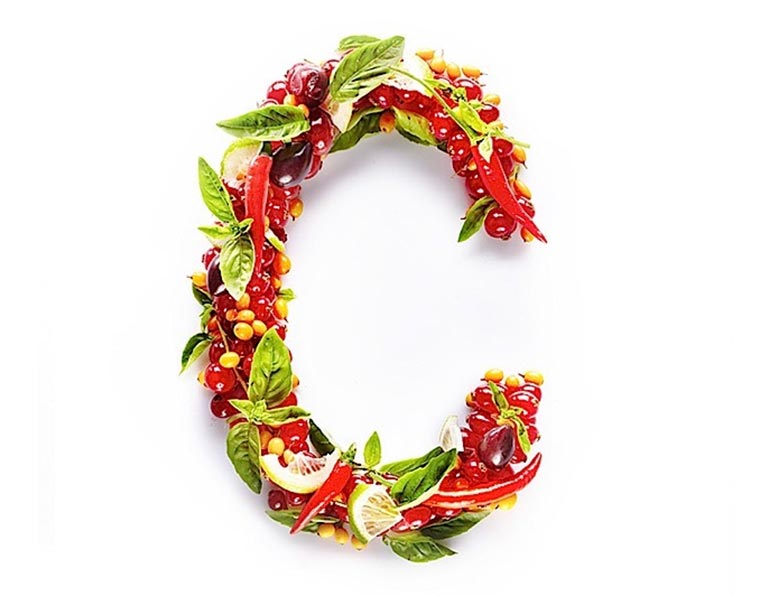
Food Typografie: Vitamine
Food Typografie: Vitamine Vitamin-Typography_01
Juliya Malanuk gibt Vitaminen ein Gesicht. Okay, zumindest eine kreative Nachbildung ihrer Abkürzungen. So bekommen wir nicht nur tolle Bilder zu sehen sondern auch Informationen darüber, in welchen Früchten und Lebensmitteln sich die genannten Vitamine und Mineralstoffe denn nun befinden. Pro-Tipp: vom Sattsehen bekommt ihr keine Vitamine. Aber fast.